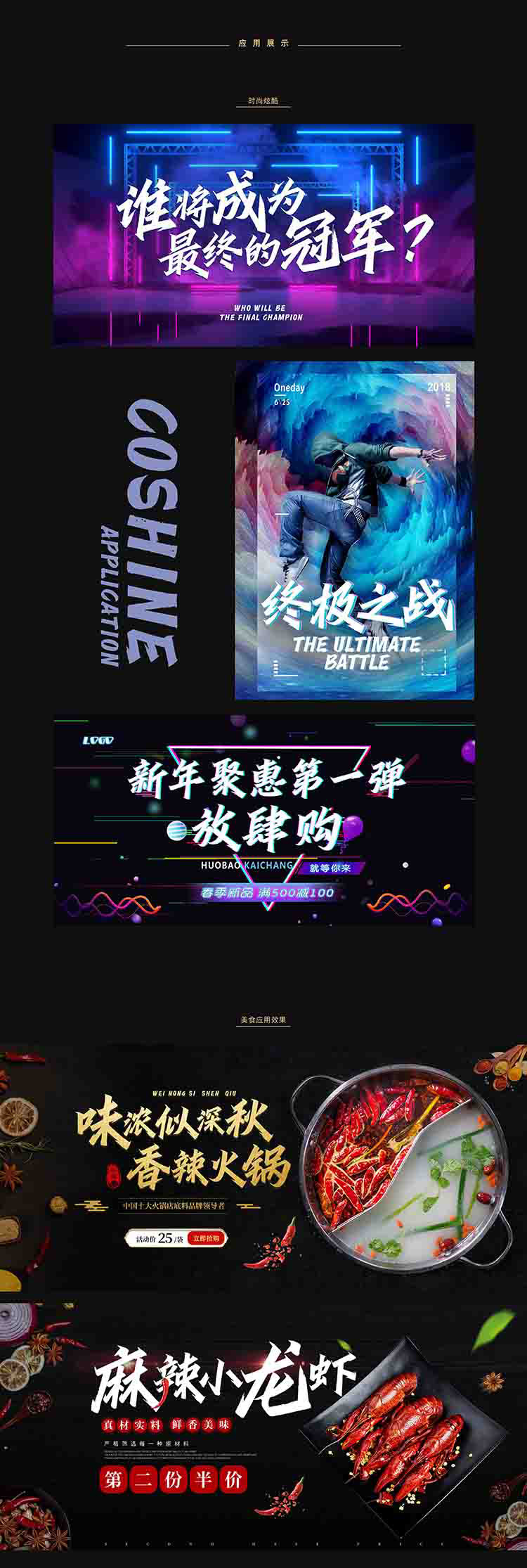
方正字迹-惊鸿体
字体品牌: 方正字迹 设计师:曹基殿 字体分类:创意字体、创意书写 字体属性:精品字 字符集:大陆简体(GB2312-80)、简繁扩展(GBK) 发布时间: 2020
这是一款结合了速度与力量的字体,大气醒目、笔触锋利、气势上扬,不仅适用于横向、纵向的排版,还方便了字与字之间的穿插,满足当今商业化应用的需求。适合于影视综艺、电商、包装、品牌名称、各类商业海报、游戏、户外广告标题等。